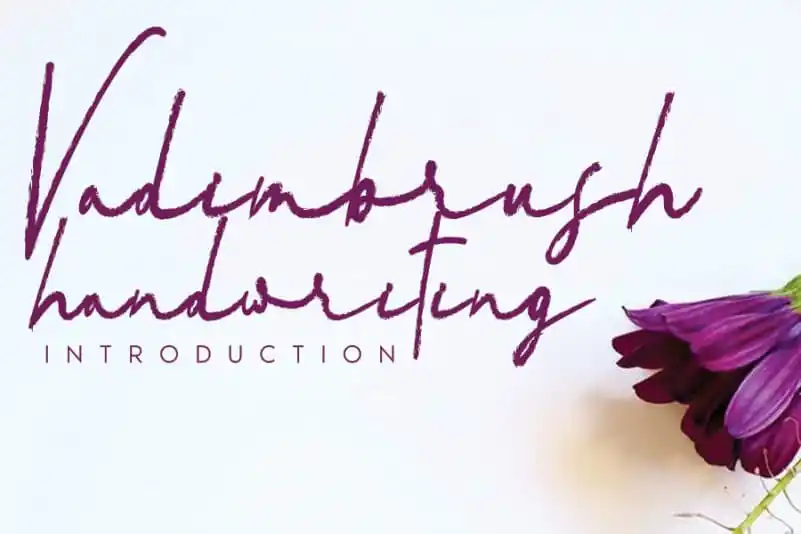
Vadimbrush Brush Font – Download Grátis
Vadimbrush Brush Font é uma fantástica e singular fonte feita à mão, projetada com a ajuda de um belo pincel pen. Esta tipografia única não apenas adiciona um toque encantador aos teus trabalhos criativos, mas também faz eles viverem em sua própria essência. Seja para logotipos vibrantes e texturas modernas ou gráficos alegres e divertidos, esta fonte tem o poder de transformar ideias em realidade, oferecendo um toque especial que faz toda a diferença na sua identidade visual. Experimenta-a agora e observe como ela pode enriquecer os teus projetos.